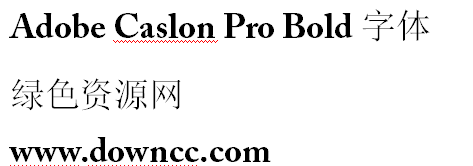
adobe caslon pro bold是一款加粗的常規(guī)西方字體,字跡簡(jiǎn)明端正,加粗后讓字體更加鮮明吸人眼光,如果你對(duì)設(shè)計(jì)有比較高的要求,不妨來(lái)綠色資源網(wǎng)免費(fèi)下載使用!
adobe caslon pro bold是adobe caslon系列字體中的加粗常規(guī)字體,有著大方得體、端莊嚴(yán)謹(jǐn)?shù)淖煮w風(fēng)格,字體加粗后,讓英文書(shū)寫(xiě)更加醒目,給人獨(dú)特的視覺(jué)好感,可廣泛運(yùn)用于藝術(shù)設(shè)計(jì)、廣告創(chuàng)意、排版印刷、海報(bào)設(shè)計(jì)等各個(gè)方面。
adobe caslon系列包括Adobe Caslon Italic、Adobe Caslon Bold Oldstyle、Adobe Caslon Ornaments、AdobecaslonW01-Bd、AdobeCaslonW01-It、AdobeCaslonW01、Adobe Caslon Pro、AdobeCaslonW01-BdIt、Adobe Caslon Pro Italic、Adobe Caslon Pro等,adobe caslon pro是比較受歡迎的一款粗體。